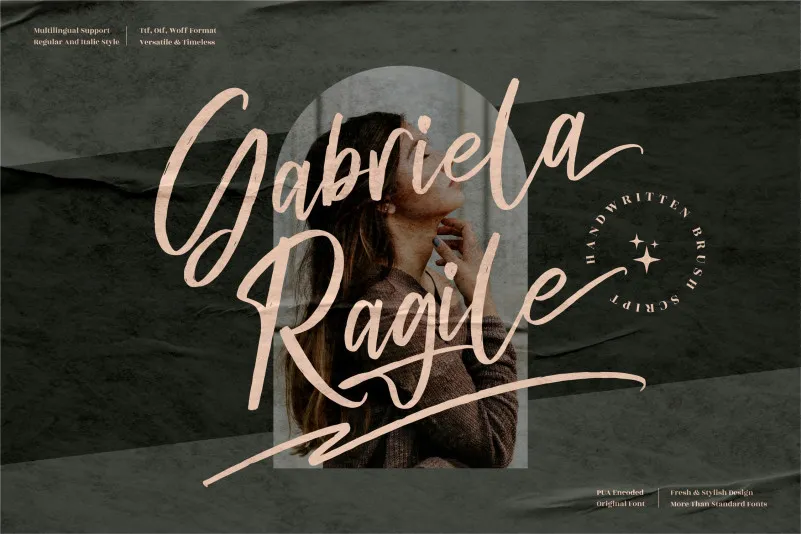
Gabriela Ragile Font – Download Grátis
A Gabriela Ragile Font é perfeita para designers em busca de uma letra de alta qualidade que se adapta a diversos projetos. Essa elegante e profissional fonte premium foi criada especificamente para adicionar um toque de luxo a sua próxima criação. Ideal para aplicações como logomarcas, embalagens de produtos, capas de livros ou cartões de visita, essa fonte oferece uma personalidade única e sofisticada que certamente impressionará seu público-alvo. Com um design cuidadosamente elaborado, a Gabriela Ragile Font garante que todos os detalhes sejam perfeitos para qualquer projeto em que você a use. Seja qual for o seu propósito, a Gabriela Ragile é uma escolha inegável para quem procura garantia de resultado impecável e um toque diferenciado no design.